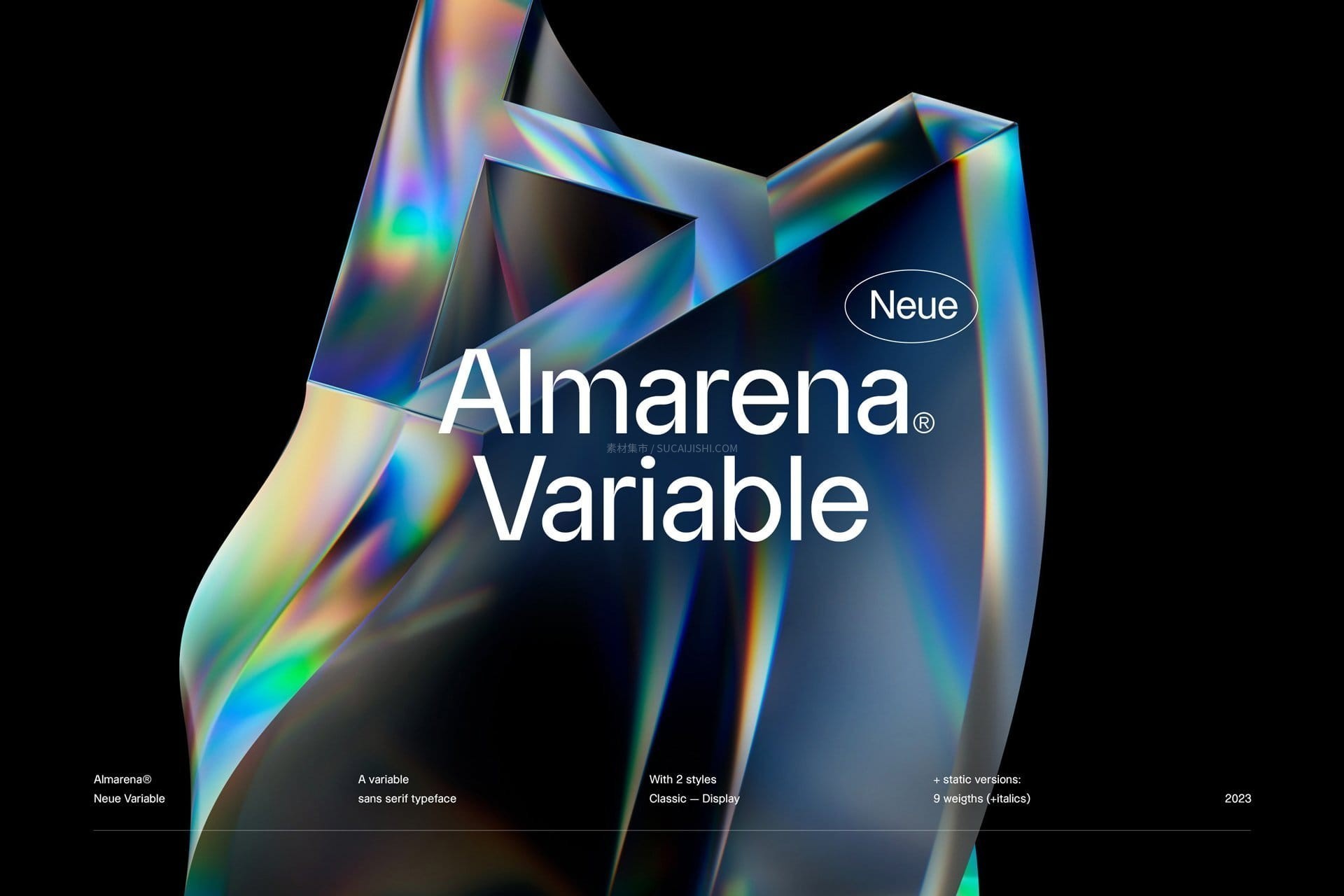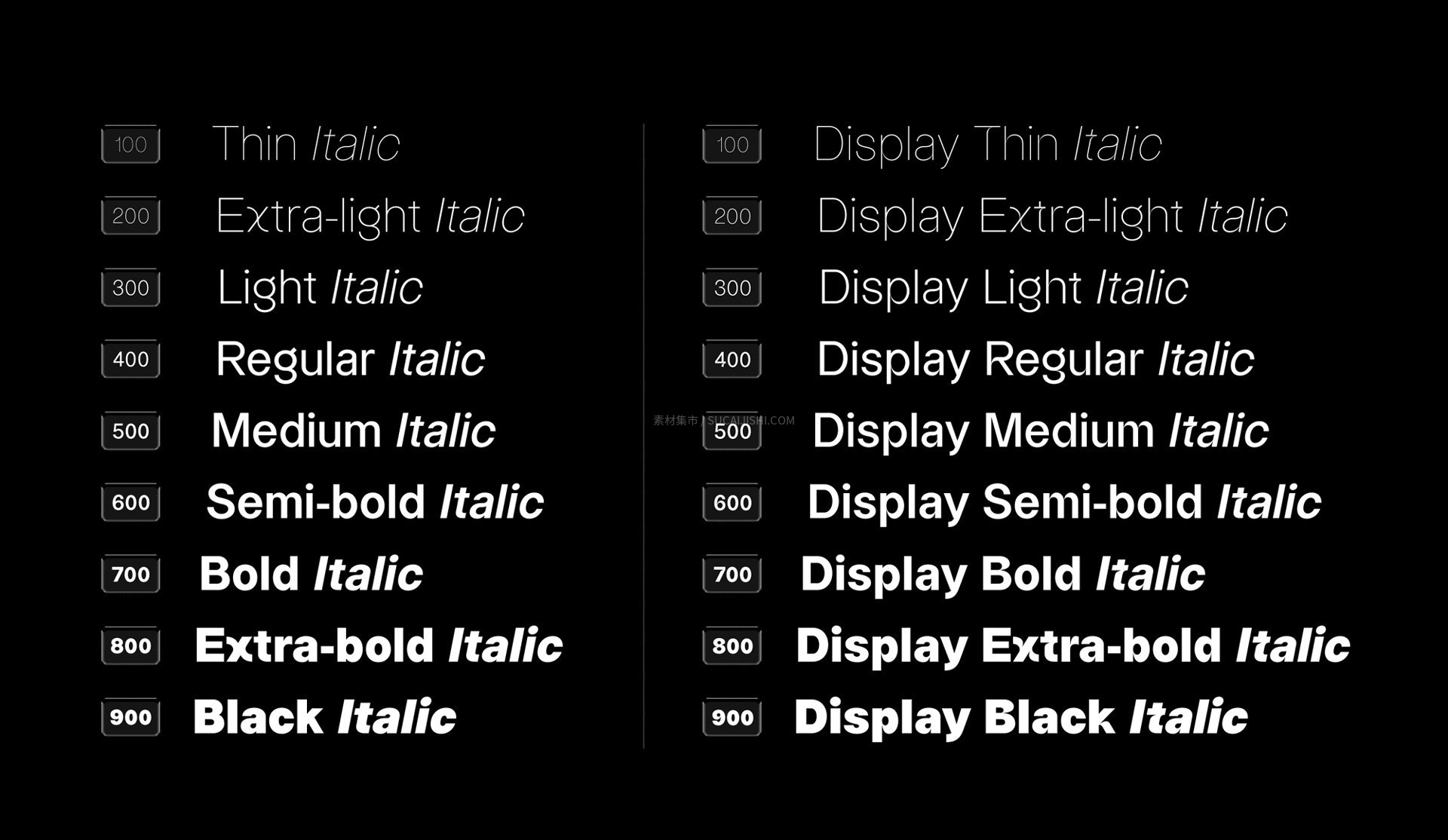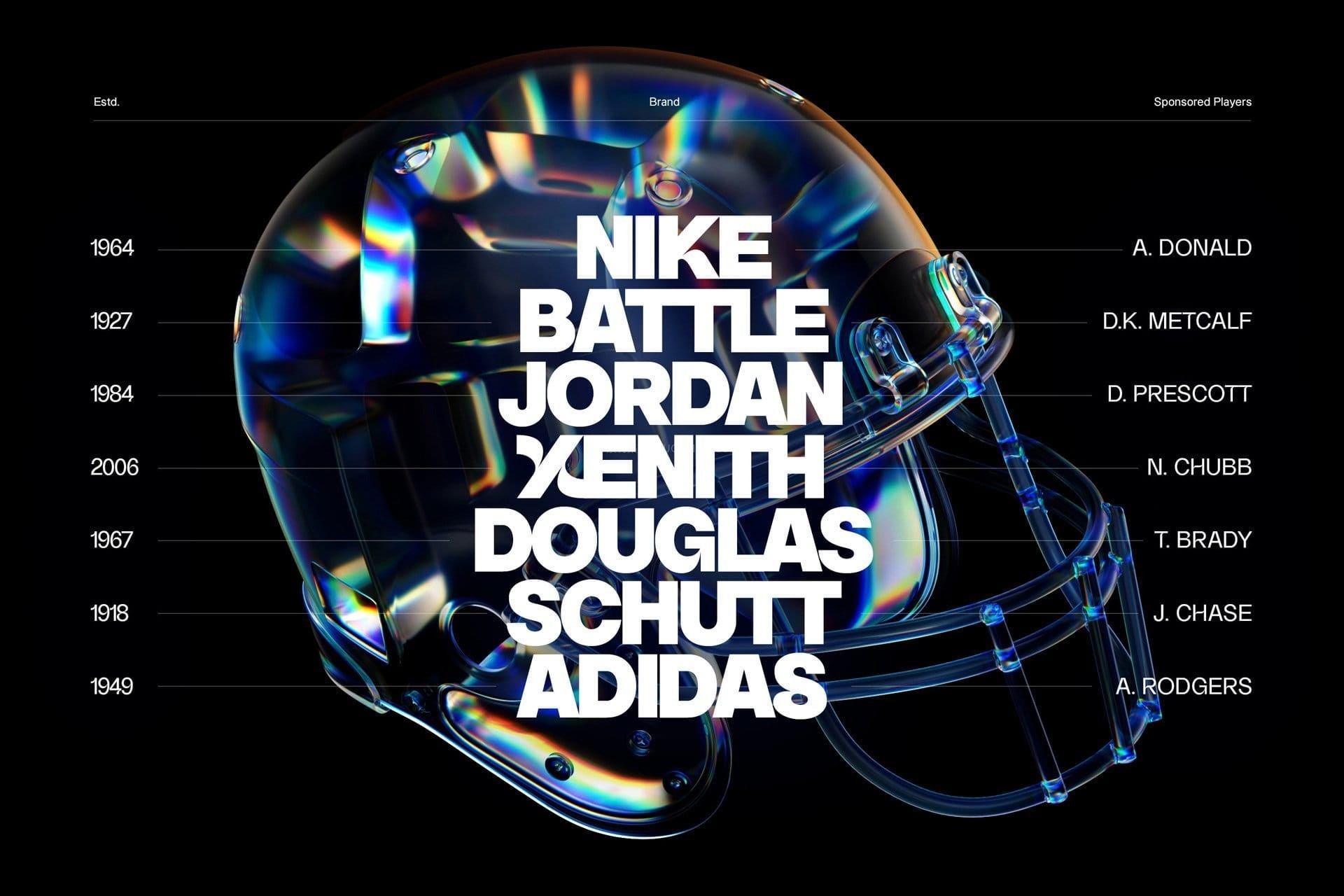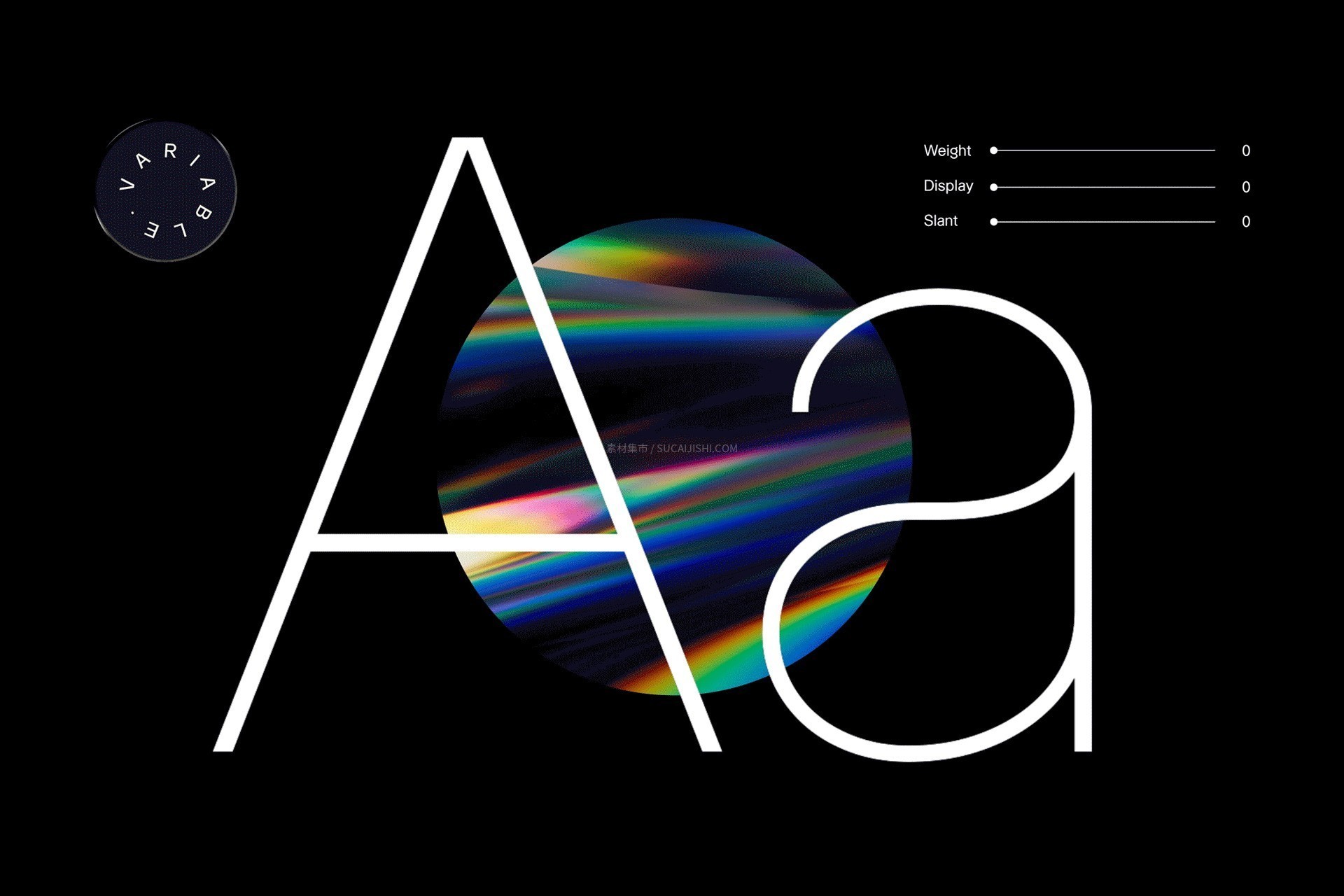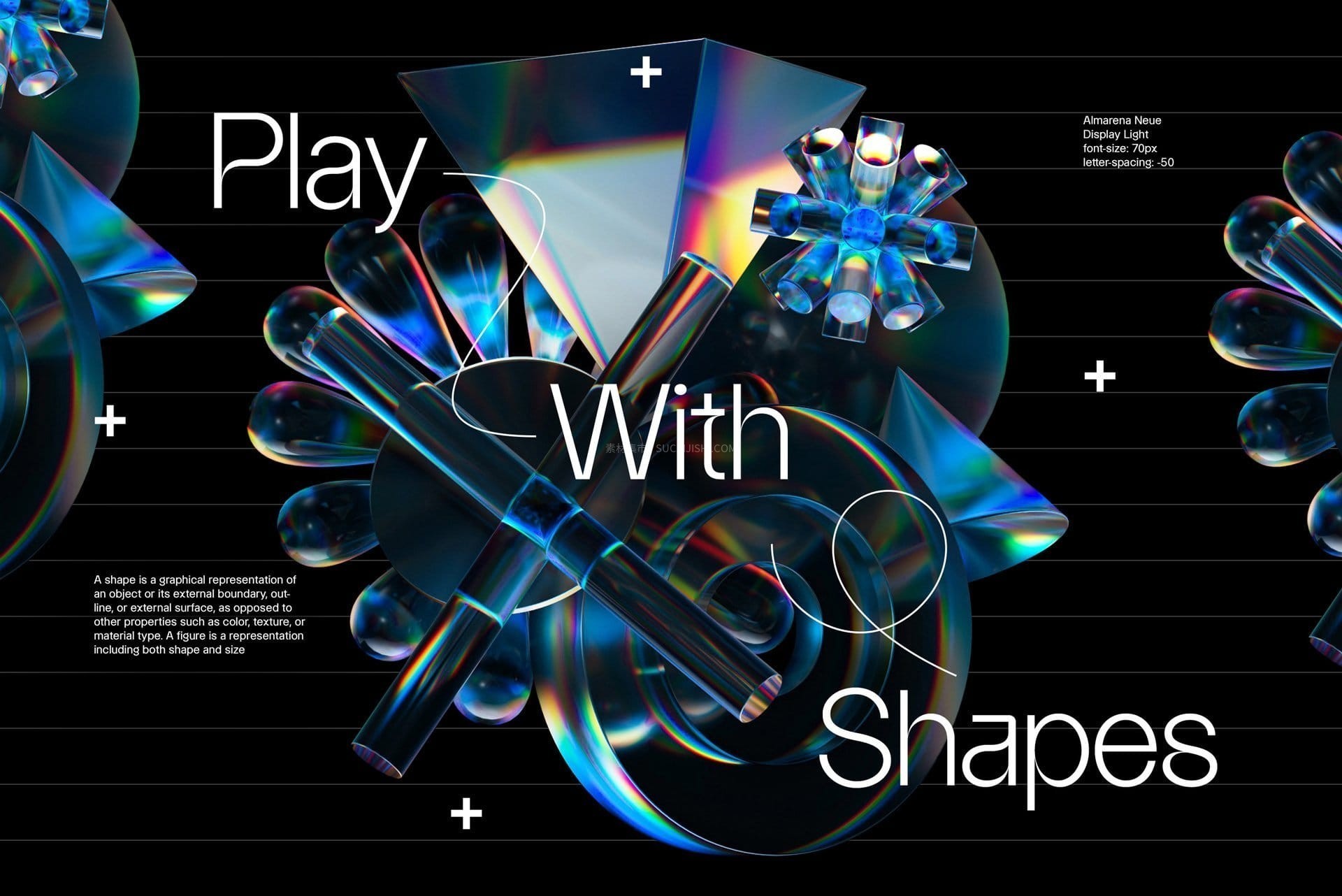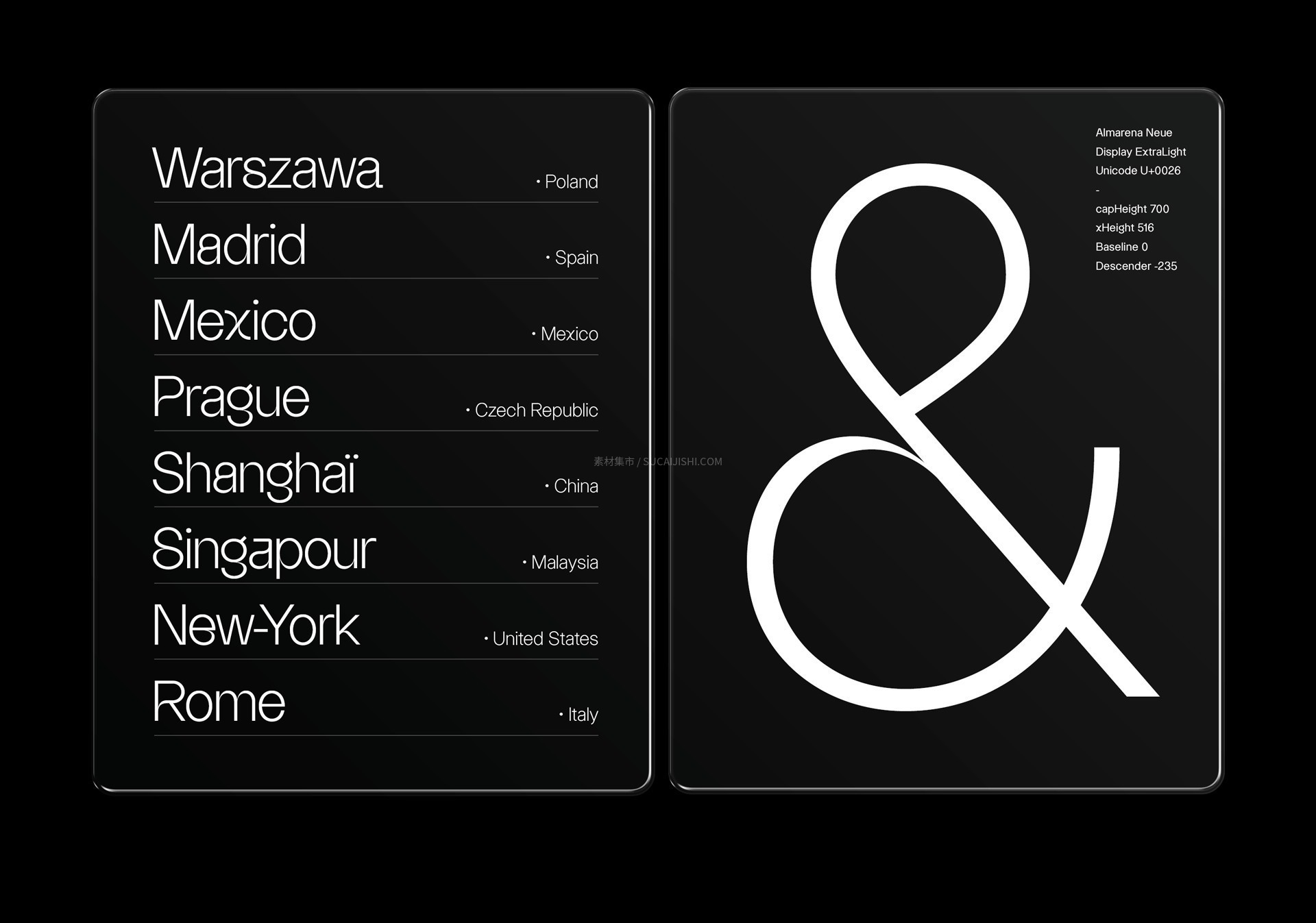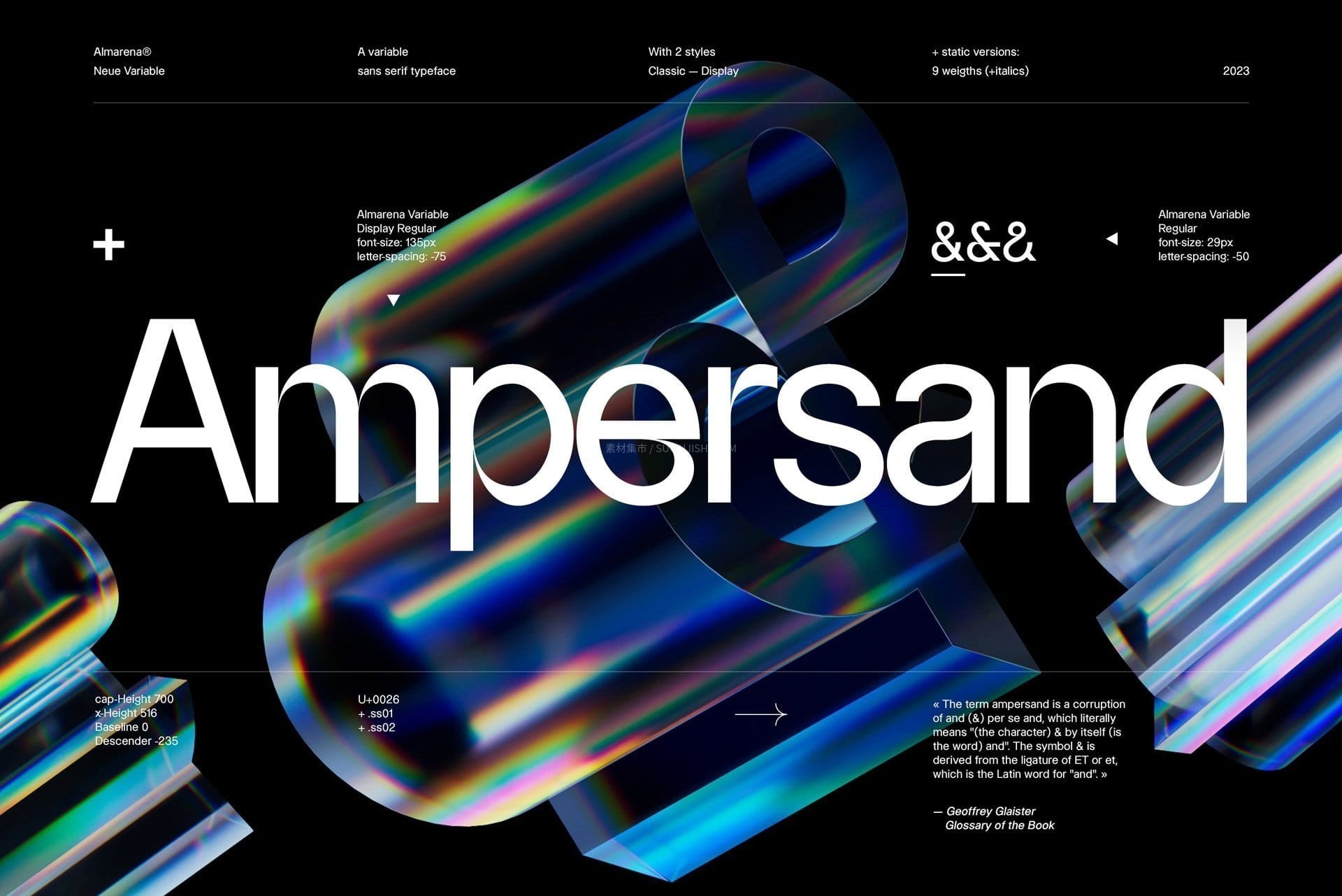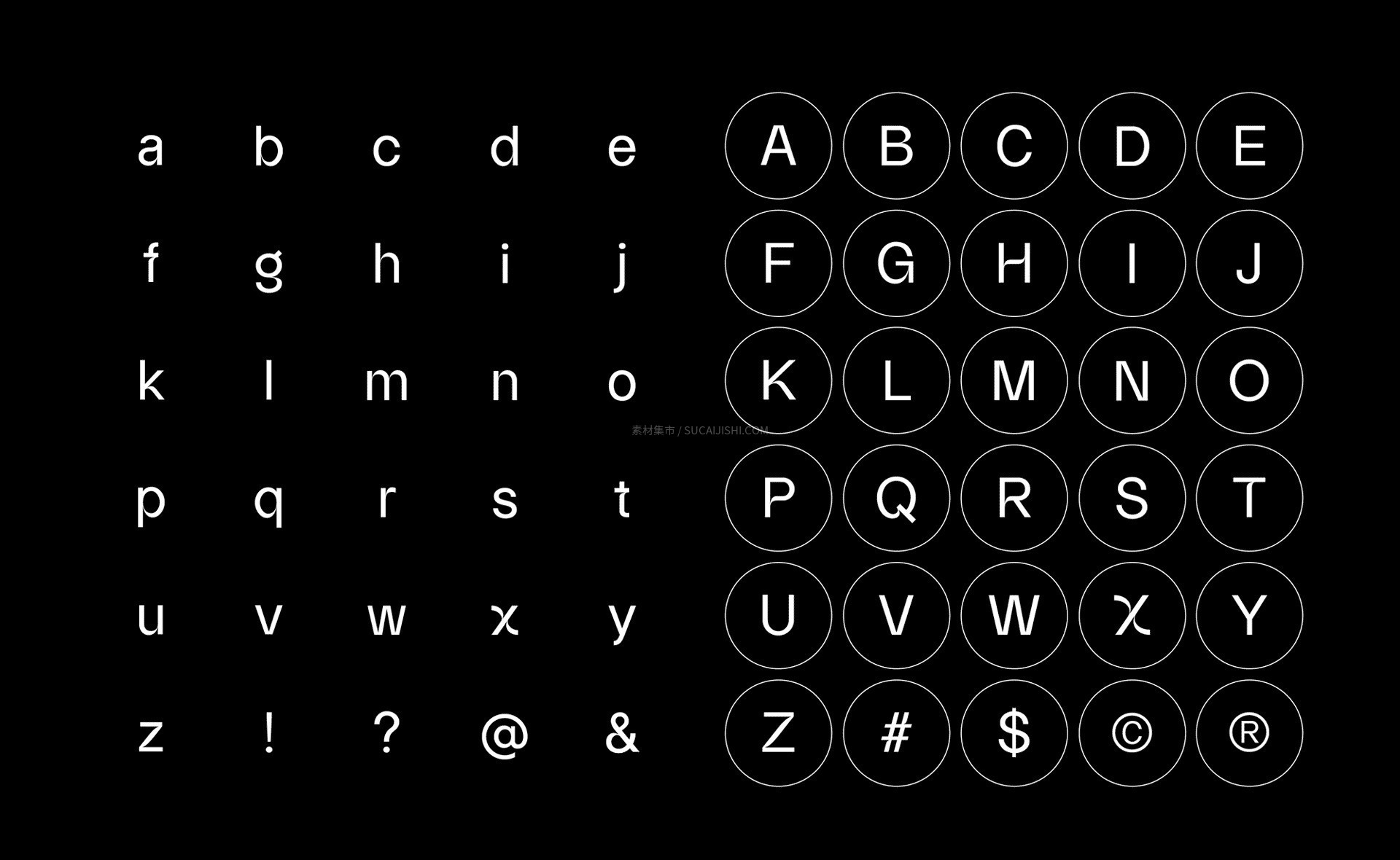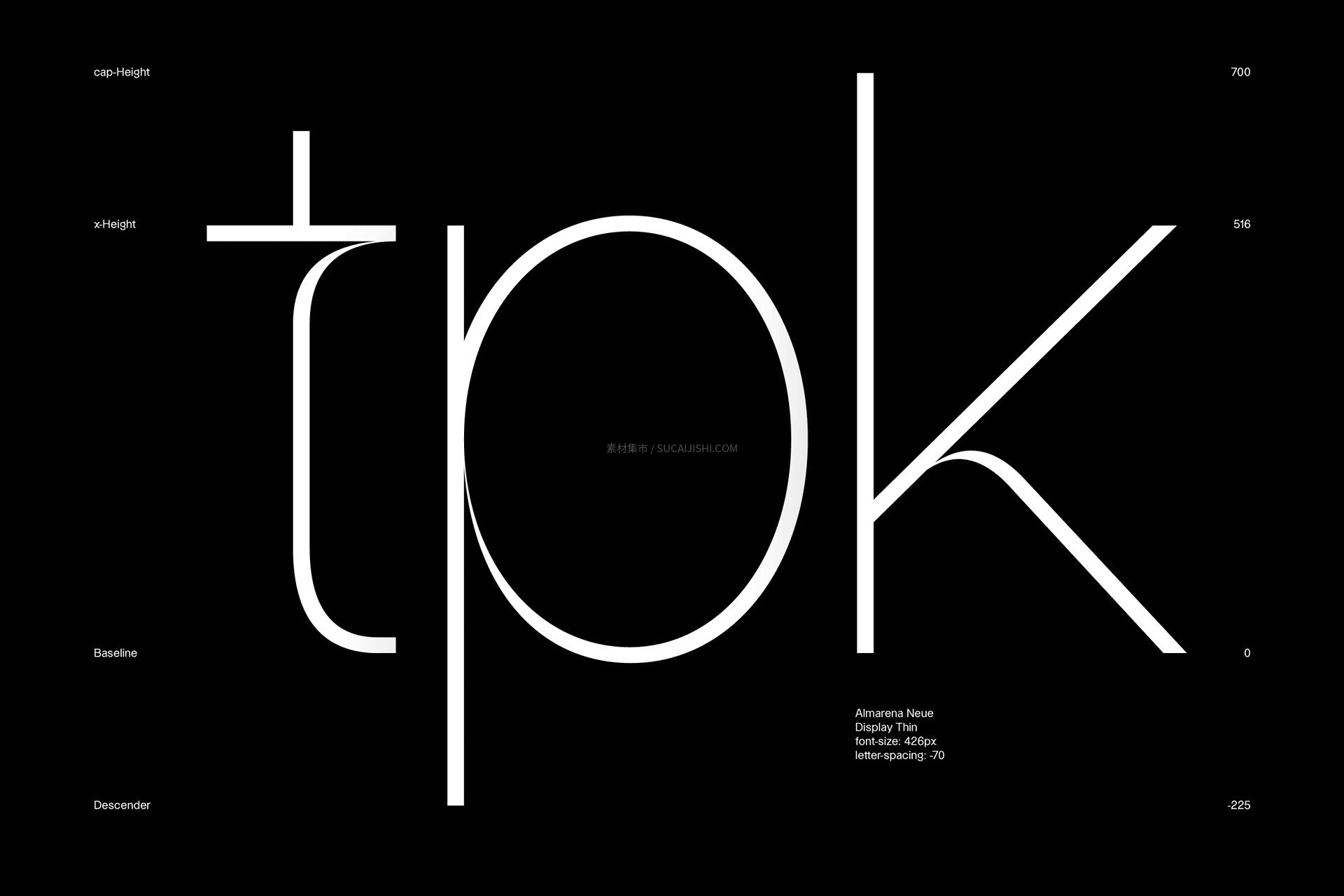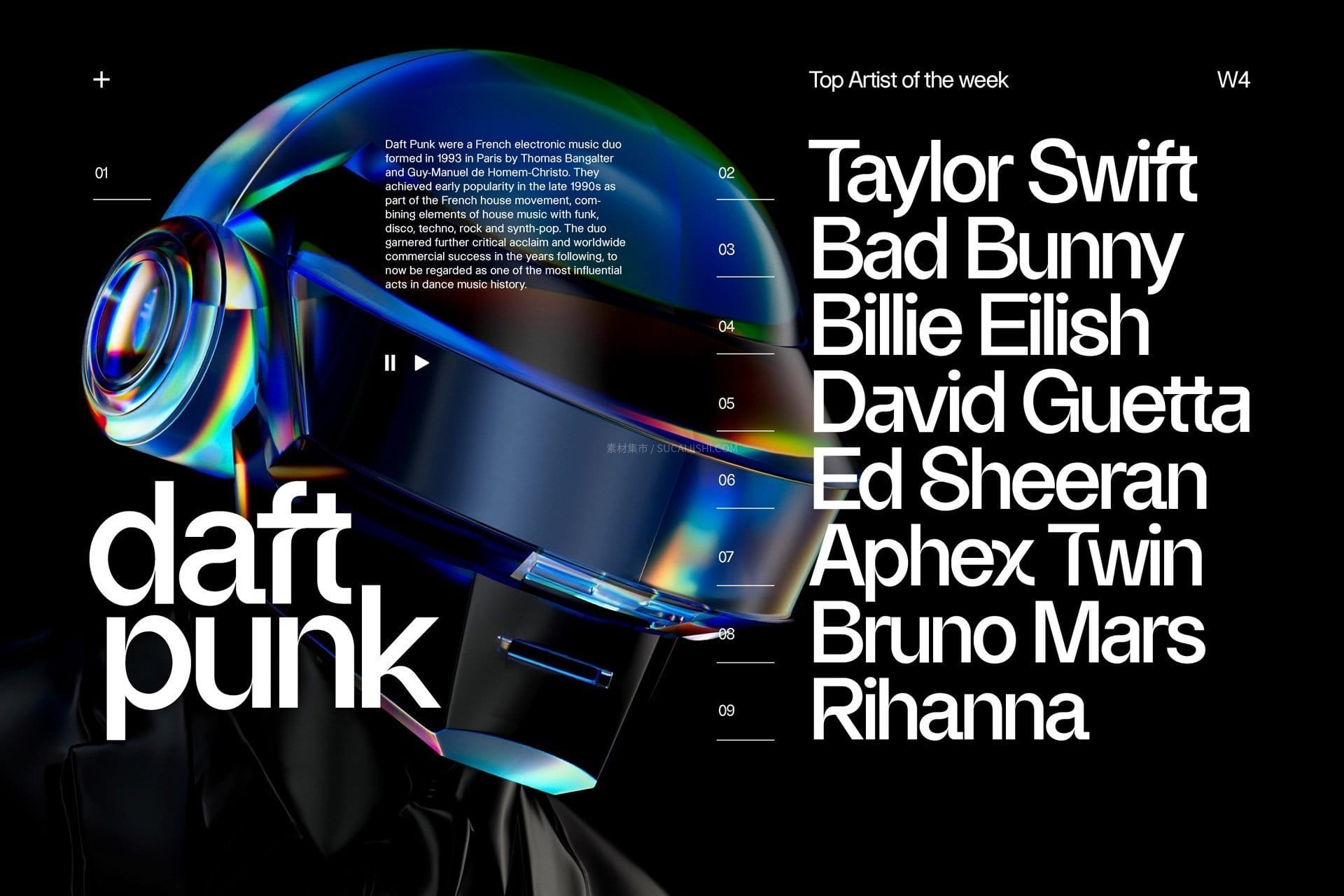
Almarena 全系列字体套件(46款静态+可变字体)
Almarena Neue® 是一款源自经典并为现代视觉环境重新诠释的优质字体系列。这套包含46款静态与可变字体的合集,完美融合了现代感、高易读性与强烈的原创性。它的字符设计严谨而精准,从沉稳的“A”到饱满的“X”,既坚实又充满独特魅力,能够经受住时间的考验,完美彰显你的品牌特质与设计品味。